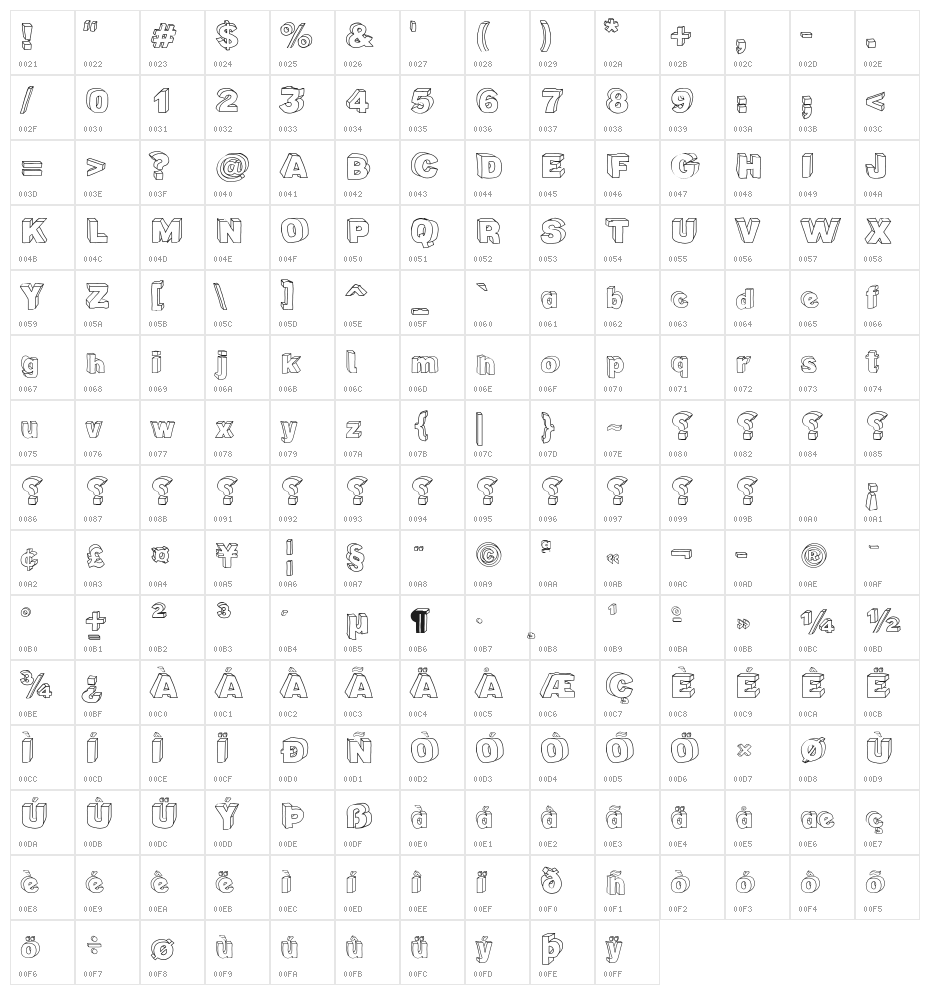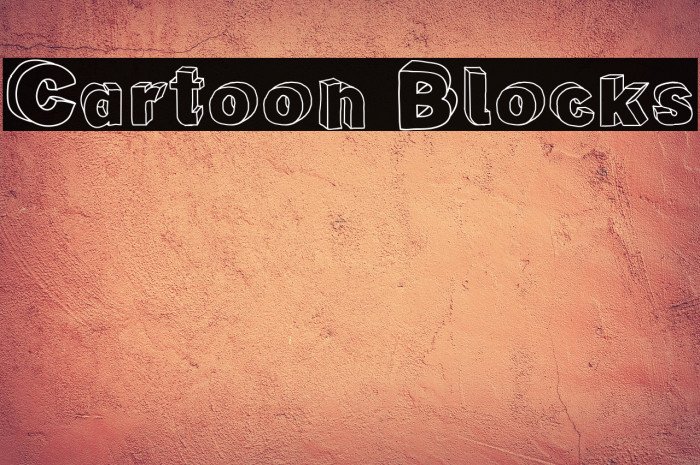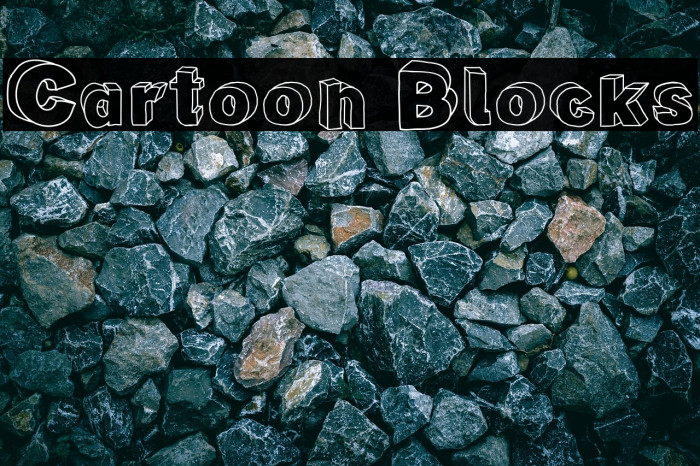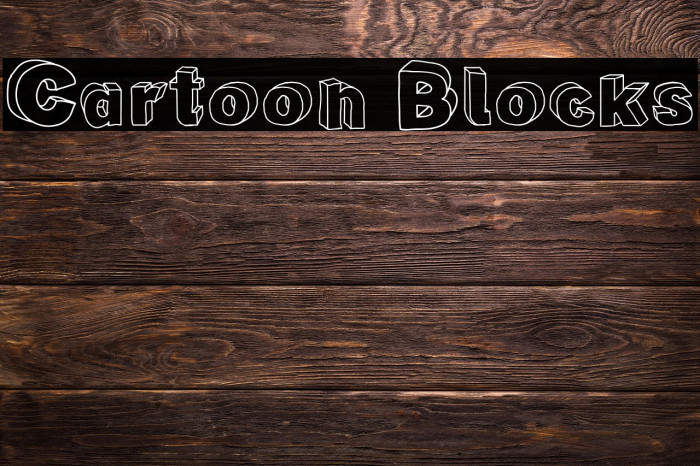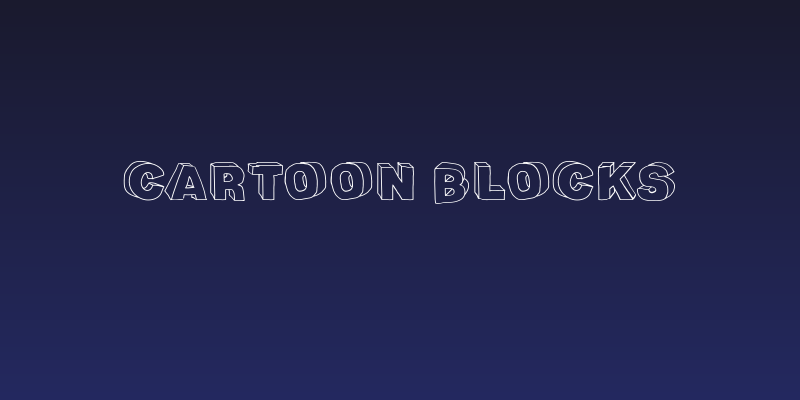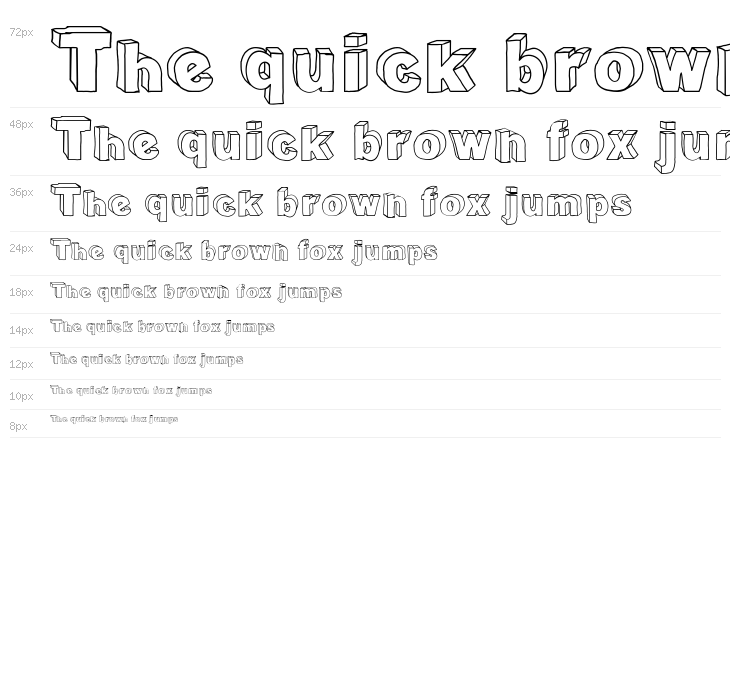
Cartoon Blocks Font
| Nom | Cartoon Blocks |
| Style général | Playful, Cartoonish, Bold |
| Projets proposés | Ideal for children's books, comic strips, playful branding, and eye-catching posters. |